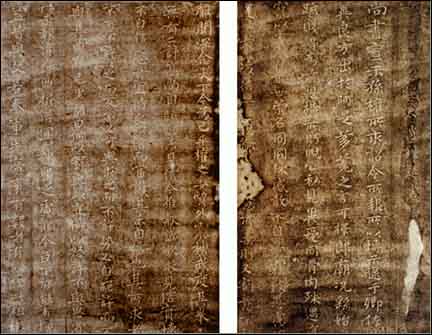
钟繇
钟繇简介
三国魏书家,字元常。颖川长社(今河南长葛)人。或作许昌人。历官侍中尚书仆射,封亭东武侯。魏初任相,明帝时迁太太傅,世称“钟太傅”,卒谥成侯。书学曹喜、刘德升、蔡邕。其正楷书法独步当时,自言精思学书三十年。所作秀美典雅,幽深无际。
他所处的正是隶楷错变的时代,正如元袁裒《总论书家》所谓:“汉魏以降,书虽不同,大抵皆有分隶余风,故其体质高古。”因此在他的真书中也带有浓厚的隶意。他的小楷体势微扁,行间茂密,点画厚重,笔法清劲,醇古简静,富有一种自然质朴的意味。唐朝张怀瓘《书断》评曰:“真书古雅,道合神明,则元常第一。”又云:“元常真书绝妙,乃过于师,刚柔备焉。点画之间,多有异趣,可谓幽深无际,古雅有余,秦汉以来一人而已。”钟繇在书法上是下过苦功的,尝自称:“吾精思书学三十年,坐与入语,以指就座边数步之地书之,卧则书于寝具,具为之穿。”可见其矢志专一的学习态度。有一次,他在当时一个著名书家韦诞家中看见一篇蔡邕论笔法的文章,苦求不得,至于捶胸吐血,曹操即以五灵丹救之。及诞死后,繇阴发其冢,始得之,书遂大进,可见他对艺术的执著追求。
其传世书作真迹已无存。《书法正传》云:“钟繇书法,高古纯朴,超妙入神。”。宋以来法帖中所刻《宣示表》、《贺捷表》、《荐季直表》、《力命表》、《墓田帖》等,都出于后人临摹。唐张怀瓘《书断》称他:“真书绝妙,乃过于师,刚柔备焉。点画之间,多有异趣,可谓幽深无际,古雅有余,泰汉以来,一人而已。”
《宣示表》
《宣示表》局部
三国时期曹魏 钟繇 楷书 荐季直表16x121宋拓
晋 钟繇 淳化阁帖宣示表小楷29x69
三国钟繇小楷荐季直表